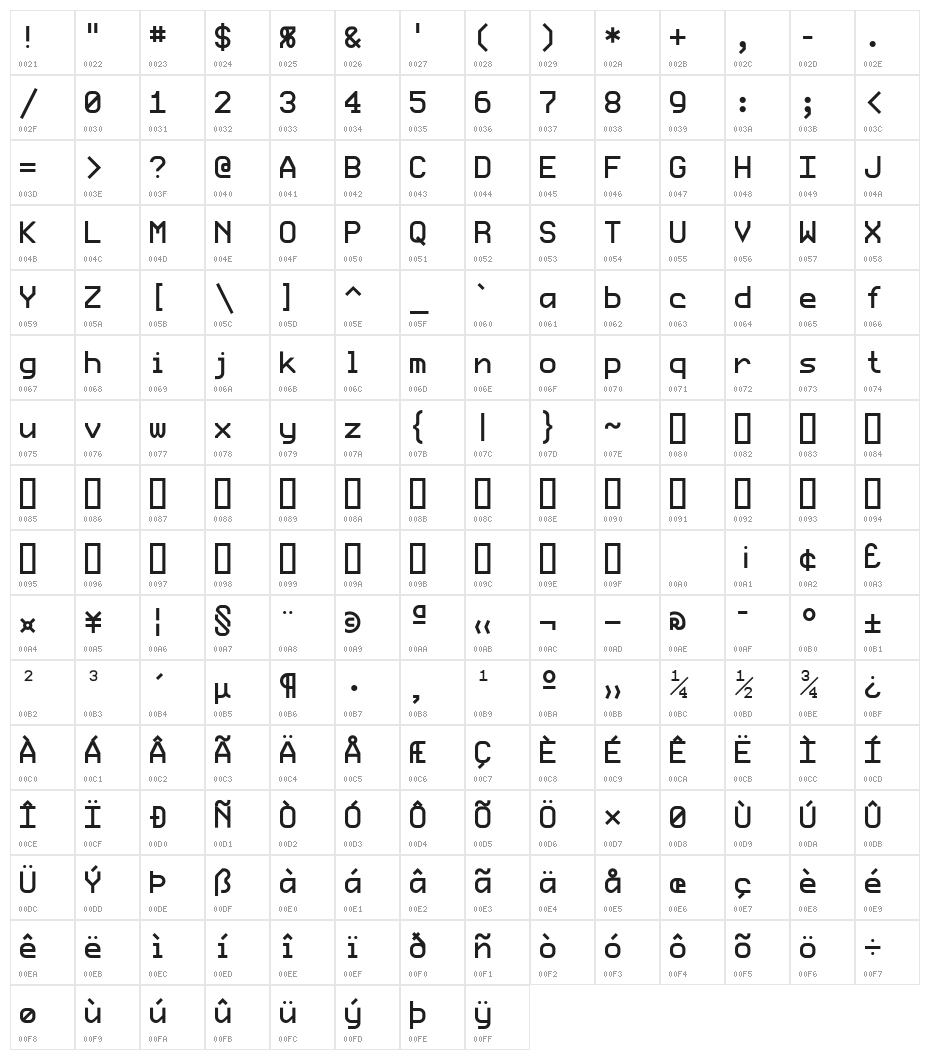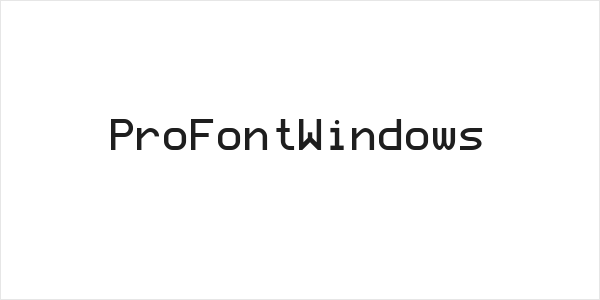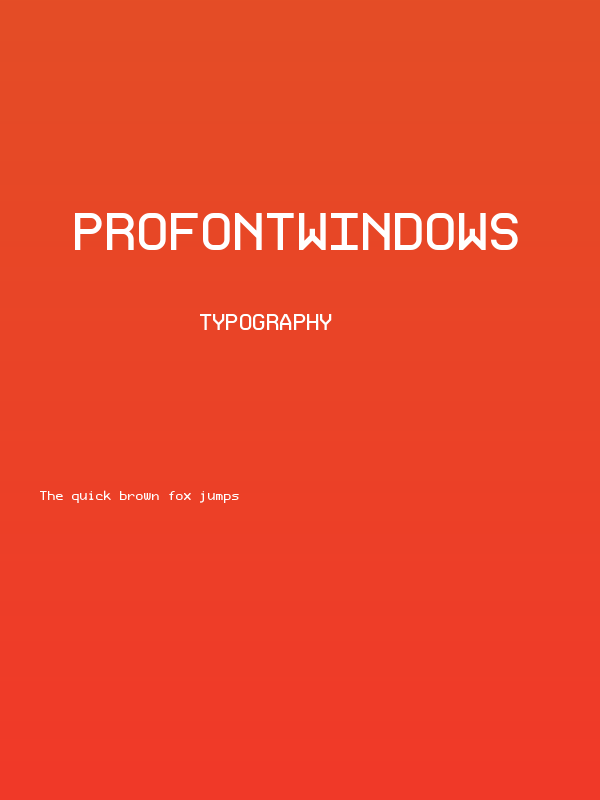
ProFontWindows Font
| Spaziatura caratteri | Normal |
| Caso d'uso | Coding, Technical documentation |
| Progetti proposti | Suitable for coding environments, technical documentation, data visualization, and any project requiring precise alignment. |
| È fissato Pitch | Yes |